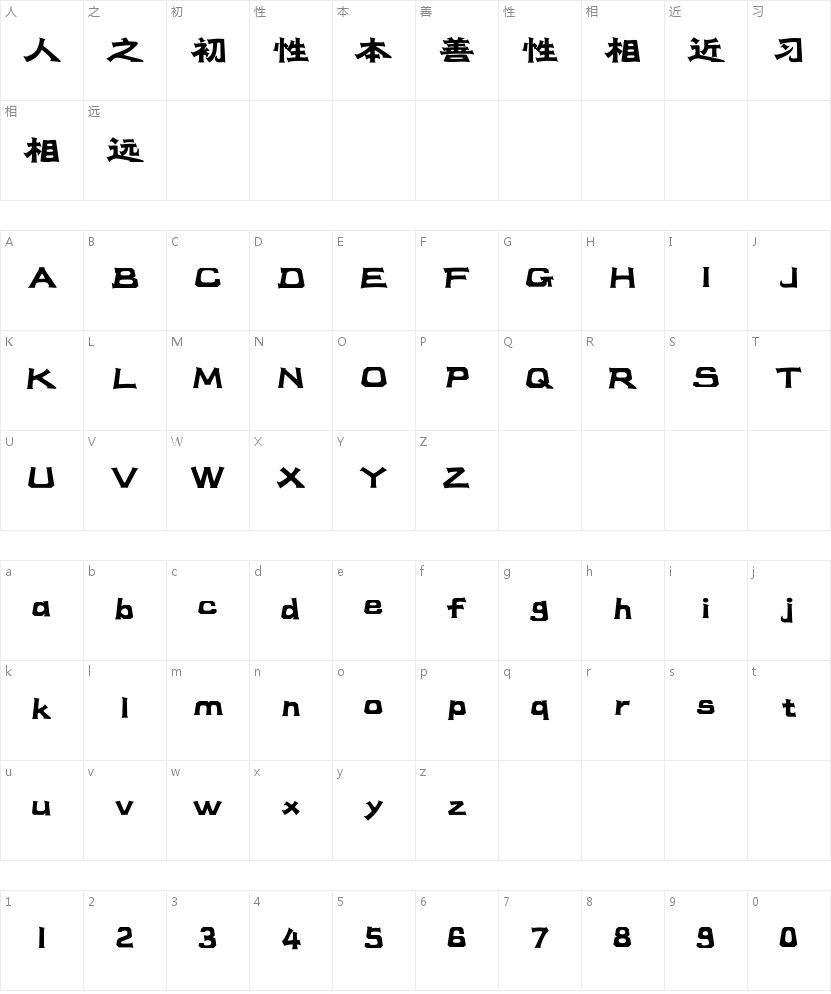
汉仪神工体简是一款由汉仪字库设计师所创作的字体,它是汉仪神工体的简化版。该字体的设计灵感源自于古代篆书和隶书,经过大量的研究和探索,设计师们成功将传统的书法艺术与现代字体设计相结合,创造出了这款独特的字体。 汉仪神工体简的特点在于其较为简洁的线条和优美的曲线,具有非常高的辨识度和美感。与汉仪神工体相比,汉仪神工体简更加适合用于印刷和屏幕显示等数字媒体上,因为它的字形结构更加紧凑,排版效果更加稳定。 汉仪神工体简的字形优美、雅致,适用于多种场合,如书籍排版、广告设计、标志设计等。它的字形设计独特,同时具有时代感和传统美感,是一款非常优秀的字体。文件名:HanYiShenGongTiJian-1.ttf
汉仪神工体简是一款非常不错的手写艺术字体,具有很好的视觉感,适合于文化类的宣传设计、商业类品牌的广告和产品包装设计以及个性化文字排版等较多场景。